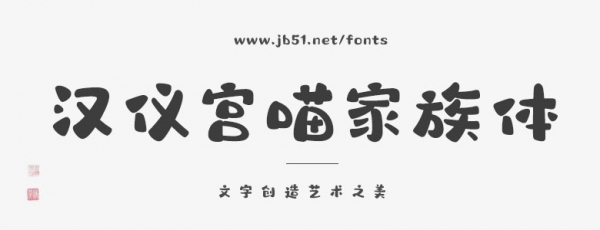
漢儀宮喵家族體 W,以故宮貓為原型,塑造了一群可愛的家族成員,講述中國傳統(tǒng)文化故事。
漢儀字庫為“紫禁城原住民”宮喵家族創(chuàng)作了專屬字體:漢儀宮喵家族體。這款字體造型似貓咪,圓滾滾胖乎乎又不失靈動活潑。筆畫圓潤飽滿,粗細對比鮮明,像貓耳朵,又像貓爪墊,柔軟有彈性。
漢儀宮喵家族體輕松、活潑、可愛,適合用于標題字體和較短文本的排版,為宮喵家族IP形象、系列圖書、動畫、廣播劇及各類聯(lián)名合作衍生產(chǎn)品增添視覺記憶點。用生動有趣的文字,講宮喵家族的故事。